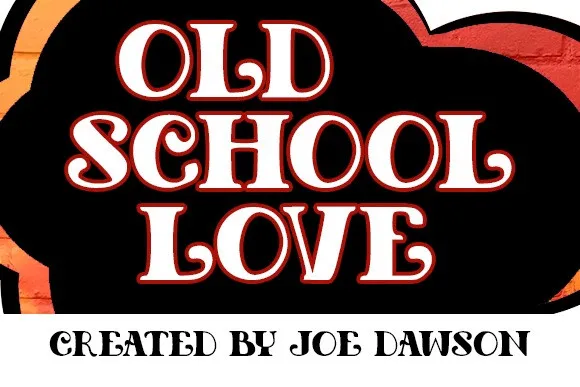
Old School Love Font – Fonte Grátis
Old School Love Font
Esta é uma nova serif font chamada ‘Old School Love’, criada pelo designer Joe Dawson na plataforma 99designs. Ela se destaca por seu moderno charme e contraste belos, oferecendo um toque de elegância ao texto. A fonte perfeito para dar um ar encantador e delicado a qualquer projeto. Seu design vintage contemporâneo é ideal para aqueles que desejam uma sensação de personalização artesanal em suas produções. Não deixe de experimentar ‘Old School Love’ para adicionar um toque único e sofisticado ao seu próximo documento ou projeto gráfico.